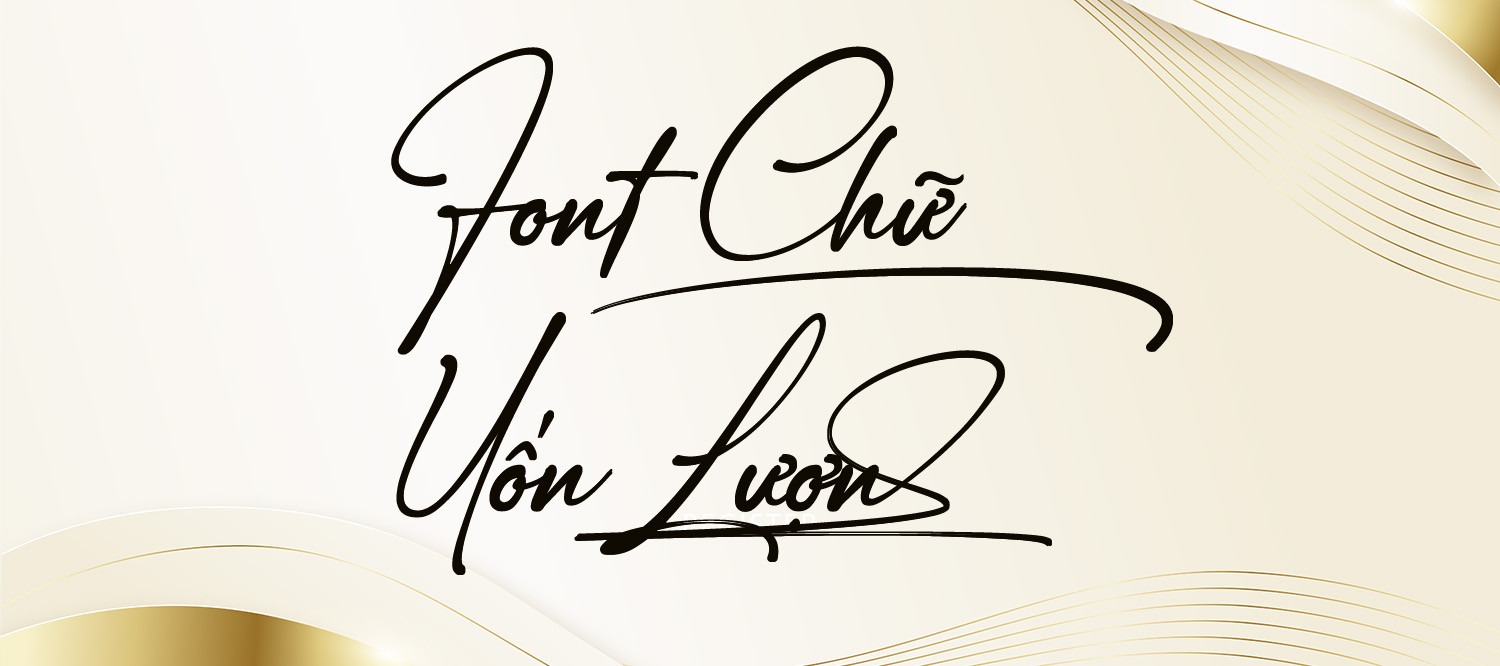
Trong thế giới thiết kế đồ họa, font chữ đóng vai trò quan trọng trong việc truyền tải thông điệp và tạo ấn tượng cho người xem. Một trong những loại font được ưa chuộng và sử dụng rộng rãi là font chữ uốn lượn. Đây là loại font có đặc điểm các đường nét mềm mại, uyển chuyển, tạo cảm giác nhẹ nhàng và tinh tế. Font chữ uốn lượn không chỉ mang tính thẩm mỹ cao mà còn giúp tăng tính nghệ thuật cho các sản phẩm thiết kế.
Font chữ uốn lượn bắt nguồn từ nghệ thuật thư pháp, một nghệ thuật viết chữ đẹp có lịch sử hàng ngàn năm. Thư pháp chủ yếu sử dụng các đường nét mềm mại, uốn lượn để tạo nên những chữ cái mang tính nghệ thuật cao. Từ nền tảng này, các nhà thiết kế đã sáng tạo và phát triển các font chữ uốn lượn để sử dụng trong các thiết kế hiện đại.
Qua các thời kỳ, font chữ uốn lượn đã trải qua nhiều giai đoạn phát triển và biến đổi. Mỗi giai đoạn đều mang đến những nét đặc trưng riêng. Font chữ này đã được ứng dụng rộng rãi trong nhiều lĩnh vực, từ thiết kế in ấn, quảng cáo, đến thiết kế web và ứng dụng di động.
Một trong những điểm nổi bật nhất của font chữ uốn lượn là tính thẩm mỹ cao. Các đường nét mềm mại và uyển chuyển tạo nên một vẻ đẹp tinh tế, dễ chịu cho người xem. Font chữ uốn lượn thường được sử dụng để tạo điểm nhấn cho các thiết kế, làm nổi bật tiêu đề, slogan, hoặc các chi tiết quan trọng khác.
Các font chữ uốn lượn thường có khả năng tùy biến cao, cho phép các nhà thiết kế dễ dàng điều chỉnh và biến tấu theo ý muốn. Từ việc thay đổi độ dày, khoảng cách giữa các chữ cái, đến việc tạo các hiệu ứng đặc biệt, font chữ này mang đến sự linh hoạt và sáng tạo không giới hạn cho người sử dụng.
Dưới đây là danh sách 06 font chữ uốn lượn phổ biến và được ưa chuộng nhất hiện nay, chắc chắn sẽ mang đến sự duyên dáng và tinh tế cho mọi thiết kế của bạn.
Font chữ viết tay TH Jalliya Việt hóa mang đến một vẻ đẹp mềm mại và thanh thoát, giống như những nét bút tay tỉ mỉ và tinh tế. Được thiết kế với các đường nét uyển chuyển, font chữ này gợi lên sự ấm áp và gần gũi, rất phù hợp cho việc sử dụng trong các thiết kế thiệp mời, thư từ cá nhân hay các sản phẩm handmade. Đặc biệt, với phiên bản Việt hóa, TH Jalliya không chỉ giữ nguyên được sự duyên dáng của nguyên bản mà còn thêm vào các dấu tiếng Việt một cách khéo léo và hài hòa, giúp người dùng dễ dàng hơn trong việc sáng tạo nội dung bằng ngôn ngữ mẹ đẻ. Font chữ này thực sự là một lựa chọn tuyệt vời cho những ai yêu thích sự mềm mại, trang nhã và cá tính trong từng nét chữ.
Font chữ chữ ký mềm mại TH Frenchasette Việt hóa là một lựa chọn tuyệt vời cho những ai tìm kiếm sự tinh tế và thanh lịch trong thiết kế. Với các đường nét uốn lượn nhẹ nhàng và các chữ cái kết nối mềm mại, TH Frenchasette mang đến cảm giác như một chữ ký viết tay đầy nghệ thuật. Phiên bản Việt hóa của font này không chỉ giữ nguyên vẻ đẹp nguyên bản mà còn đảm bảo tính chính xác và dễ đọc cho người dùng tiếng Việt. Điều này làm cho TH Frenchasette trở thành một công cụ lý tưởng cho các thiết kế thiệp mời, logo và các tài liệu cần sự sang trọng và cá nhân hóa.
Font chữ uốn lượn Mrattoos-Regular là một sự lựa chọn tuyệt vời cho những ai yêu thích sự mềm mại và tinh tế trong chữ viết. Với phong cách chữ ký mềm mại, font chữ này mang đến vẻ đẹp độc đáo, dễ dàng thu hút ánh nhìn trong các thiết kế bìa tạp chí, tài liệu quảng cáo và tờ rơi.
Mrattoos-Regular còn rất phù hợp cho các chiến dịch quảng cáo trên Instagram, các dự án thiết kế trên Canva và nhiều ứng dụng thiết kế khác, nhờ vào sự linh hoạt và các glyph hỗ trợ Unicode (PUA), giúp người dùng dễ dàng sử dụng trên mọi nền tảng. Với hơn 700 glyph, phông chữ này không chỉ đẹp mà còn đầy sáng tạo, mang đến nhiều lựa chọn thay thế độc đáo, cho phép người dùng thể hiện sự cá tính và phong cách riêng biệt trong từng thiết kế.
Font chữ TH PerfectSignature Italic mang đến một cảm giác mềm mại và thanh lịch, như những nét bút tay tinh tế trong một bức thư tay. Các ký tự trong font này được thiết kế với những đường cong mượt mà và duyên dáng, tạo nên vẻ ngoài hài hòa và tự nhiên. Sự mềm mại của nó không chỉ làm nổi bật phong cách cá nhân mà còn thể hiện được sự chăm chút và tỉ mỉ trong từng chi tiết. Đây là lựa chọn hoàn hảo cho các thiết kế yêu cầu sự trang nhã, từ các bức thiệp mời, chữ ký số, đến các logo sang trọng. Với TH PerfectSignature Italic, mỗi dòng chữ như mang theo một câu chuyện, đầy cảm xúc và cá tính.
Font chữ uốn lượn Việt hóa Jhodes là một lựa chọn tuyệt vời cho những ai đang tìm kiếm một kiểu chữ mang đậm dấu ấn cá nhân và sự tinh tế. Với những đường nét mềm mại, uyển chuyển, và các ký tự được thiết kế tỉ mỉ, font chữ này tạo nên cảm giác tự nhiên như đang viết tay thực sự. Đặc biệt, phiên bản Việt hóa của Jhodes không chỉ giữ nguyên vẻ đẹp nguyên bản mà còn hỗ trợ đầy đủ các dấu tiếng Việt, giúp người dùng có thể dễ dàng áp dụng trong các văn bản tiếng Việt một cách chuẩn xác và thẩm mỹ. Điều này làm cho Jhodes trở thành một công cụ lý tưởng cho các thiết kế đồ họa, thiệp mời, chữ ký điện tử và nhiều ứng dụng sáng tạo khác.
SVN-Janelotus mang đến một cảm giác dịu dàng và tinh tế, như những nét bút lả lướt trên trang giấy. Các đường nét trong font này mềm mại, uốn lượn một cách tự nhiên, tạo nên vẻ thanh thoát và uyển chuyển. Font chữ SVN-Janelotus thích hợp cho các thiết kế mang tính chất cá nhân hoặc nghệ thuật, từ thiệp mời, chữ ký điện tử đến những tiêu đề trang nhã. Mỗi ký tự được chăm chút tỉ mỉ, tạo nên một tổng thể hài hòa, giúp truyền tải sự tinh tế và thanh lịch trong từng câu chữ.
Nhìn chung, font chữ uốn lượn là một phần không thể thiếu trong kho tàng font chữ của các nhà thiết kế đồ họa. Với vẻ đẹp mềm mại và uyển chuyển, font chữ uốn lượn không chỉ làm nổi bật nội dung mà còn mang đến một cảm giác nghệ thuật và sáng tạo cho người xem. Việc hiểu và áp dụng đúng cách các font chữ này sẽ giúp các nhà thiết kế tạo nên những tác phẩm ấn tượng và đạt hiệu quả cao trong công việc.